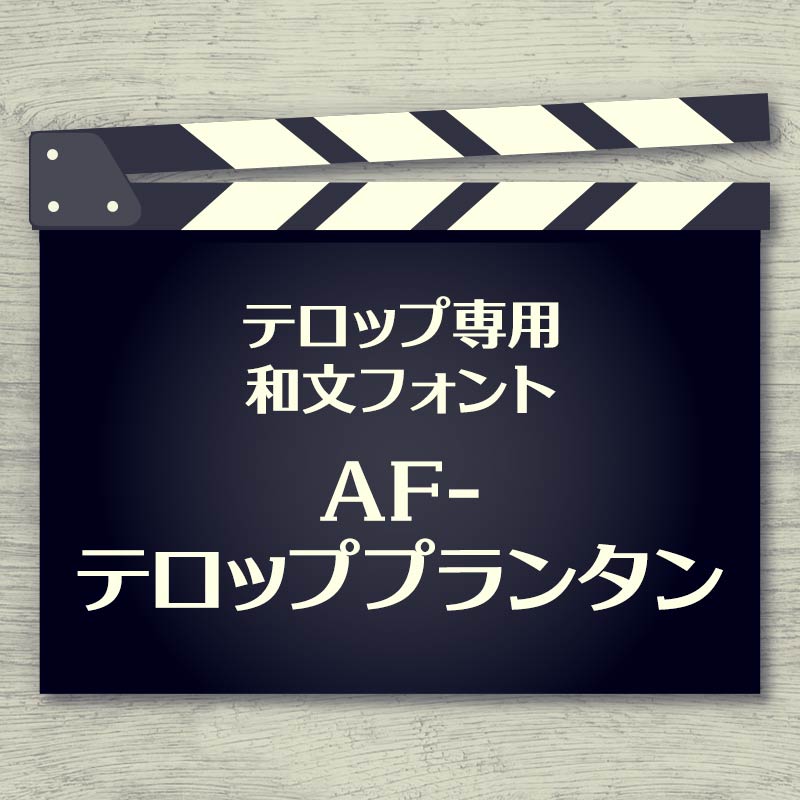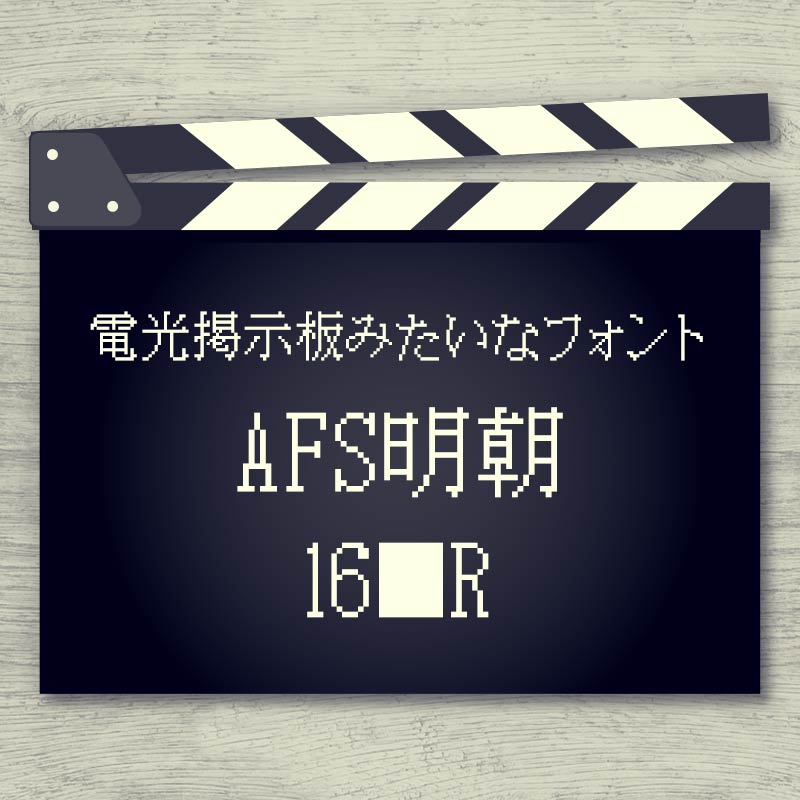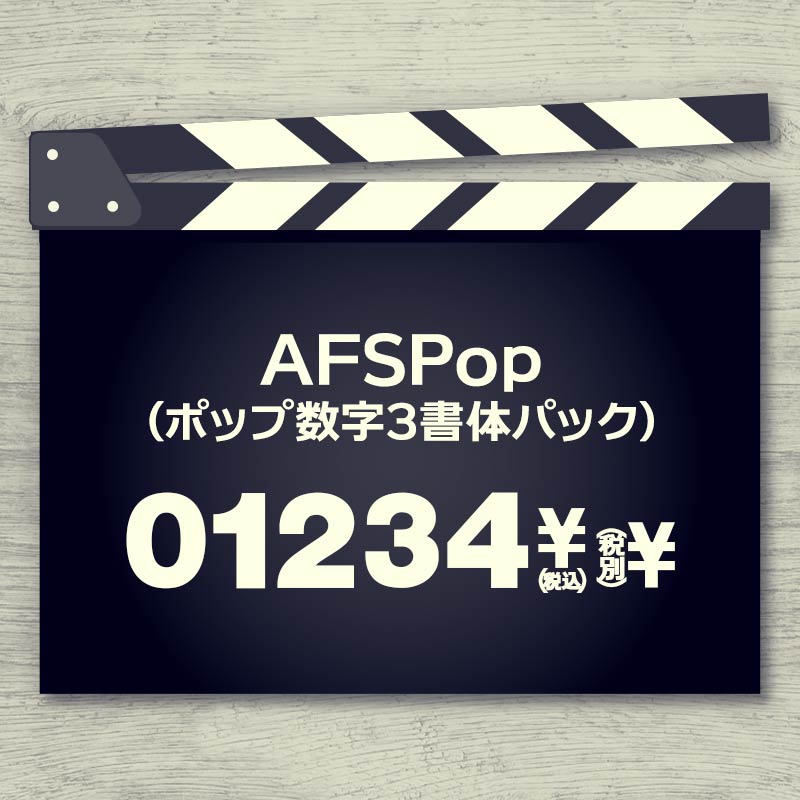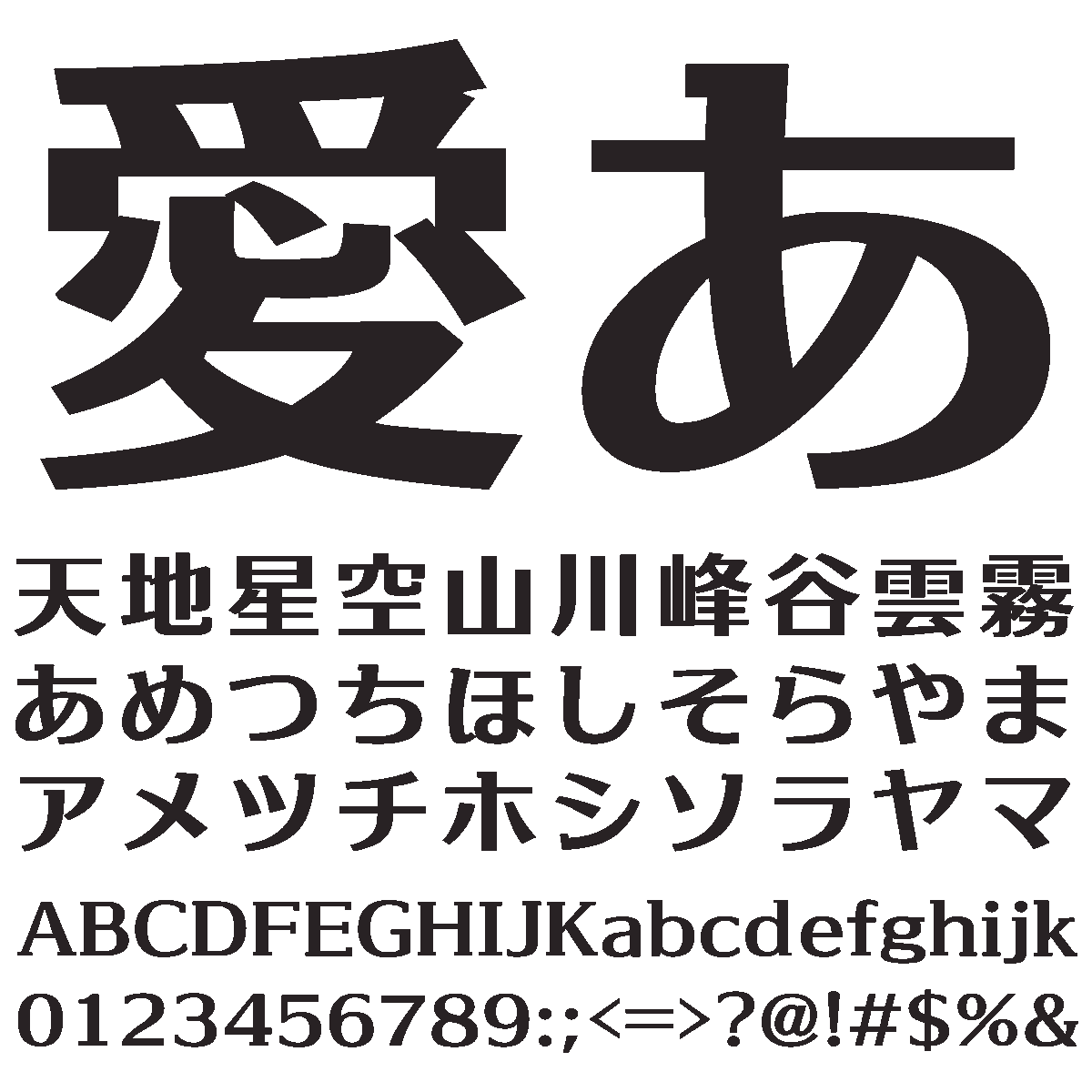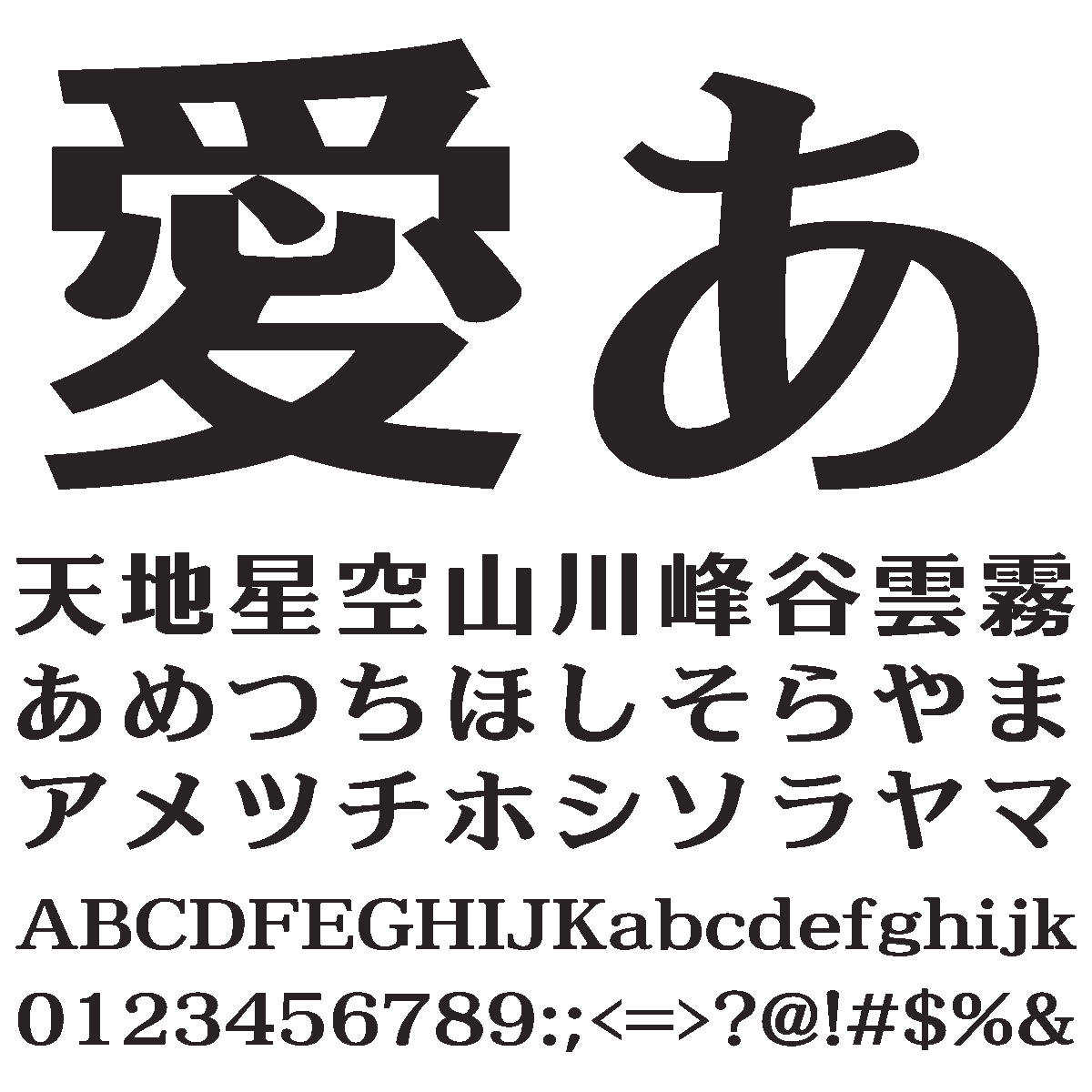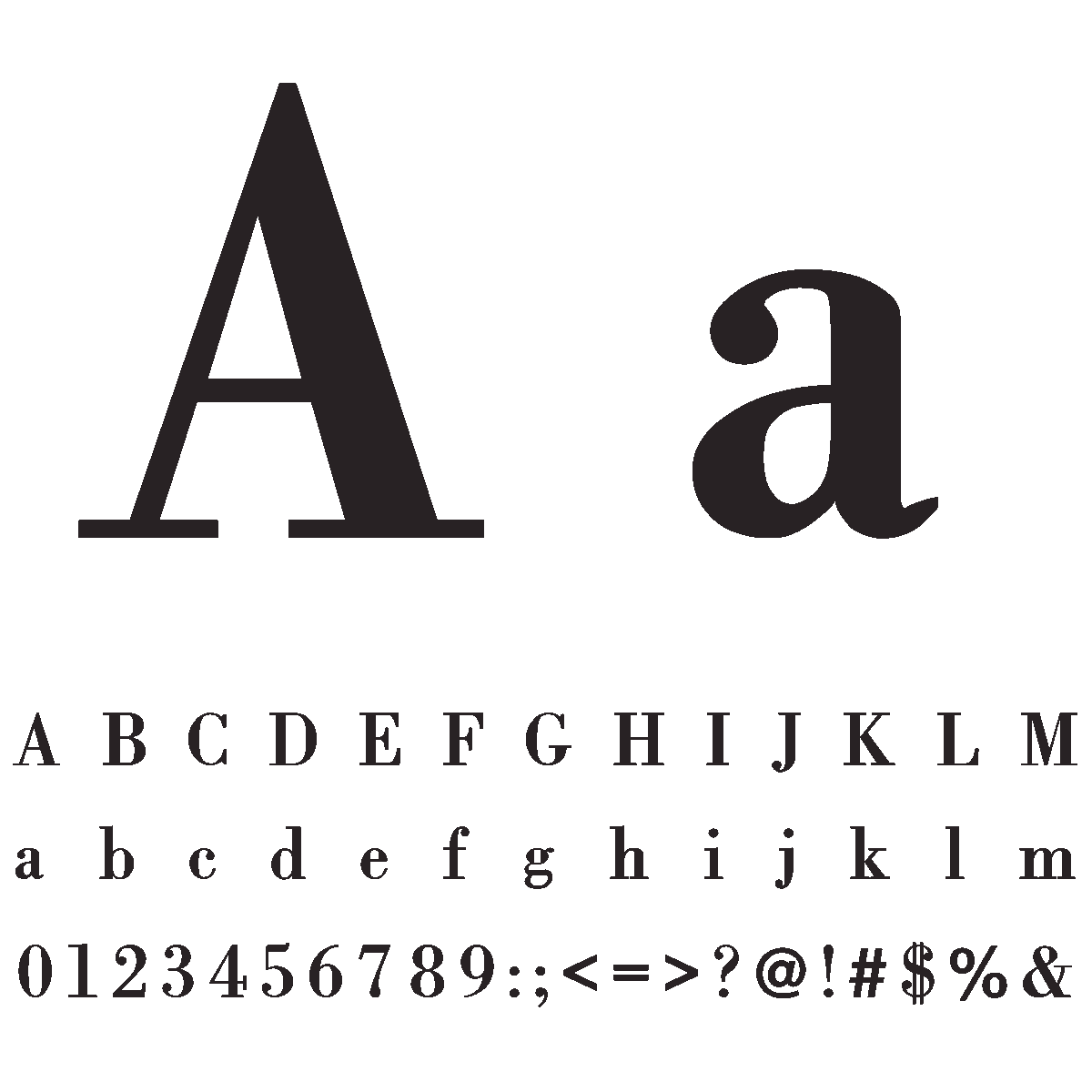
SNS動画編集で役立つフォント39セット
流行りのタテ型動画(YouTubeショート・TikTok・インスタリール)やYouTube動画制作の字幕やタイトル・感情を表すときにおすすめしたい39書体 (+特典1書体) を収録した特別セット
セット内容
●和文:19点
AFSまるご風10書体セット,テロップ/サムネイル用 AF-UVImpact,テロップ専用和文フォント AF-テロッププランタン・AF-テロップミンフォーマル,電光掲示板みたいなフォント AFS明朝16■R・AFSゴシック16■R,AFS漢字を作ろう
●平仮名:12点
AFS感情(平仮名)フォント12書体セット
●欧文:3点
テロップ専用復刻欧文 AF-TelopBod・AF-TelopEuro,AFS復刻欧文フォント AFSFutuM
●数字:3点
AFSPop (ポップ数字3書体パック)
●その他:2点
AFSDisplay (表示器風フォントシリーズ2書体パック)
●特典フォント (Windows用)
AFSデジタル放送TV用ARIB外字付きフォントDB (AFSARIBDB)
動画に文字や字幕を入れるメリット
動画編集にフォントを取り入れることで、さまざまなメリットと効果が期待できます。これから制作する動画をより魅力的にするために、フォントの選択を一度見直してみてください。それにより、動画の質が向上するかもしれません。
視覚的な強調
フォントは視覚的な要素で、視聴者の注意を引き、重要な情報を強調します。
情報の伝達
全ての視聴者が音声を聞くわけではありません。そのため、テキストは音声が聞こえない視聴者や異なる言語の視聴者にとって、情報を伝える重要な手段となります。
感情の伝達
フォントの種類やスタイルは、動画の雰囲気を伝える役割を果たします。例えば、楽しくカジュアルな雰囲気を出すためには、太く丸みを帯びたフォントが適しています。
視覚的な魅力と調和
動画におけるフォントは重要な視覚情報であるとともに、全体的なデザインとの調和も大切です。また、視聴者が情報を理解するためには、テキストは簡潔で明確であることが重要です。
おすすめの使い方
YouTube動画のサムネイル
使用フォント:AFSゴシックビューE_M
TikTokやshortsなどの縦型動画の文字入れ (字幕用フォント)
使用フォント:AF-テロッププランタンE2、AF-UVImpact、AFSゴシックドゥクラシックE_M
強いインパクトを与えたいシーン (装飾用フォント)
使用フォント:AFS感情-つらい、AFS感情-こわい
収録書体一覧
AFSまるご風 10書体セット
AFSオリジナルフォント35書体から10書体を厳選し丸ゴシック風の加工を施しました。
テロップ/サムネイル用 AF-UVImpact
ゲームソフトバンドル対応可能な、極太でインパクトあるユニバーサルフォントです。
元祖ユニバーサルデザインフォントであるメイリオを源流に、特徴が顕著に表れる一部の英数字ひらがなカタカナを一般的なUDフォントに近づけると共に、ひらがな字形ついては学参フォントを意識し視認性を強化しました。
テロップ専用和文フォント AF-テロッププランタン
加工フォントシリーズ (斜体/扁平/長体) に同梱されている「AFSPrintempsE.ttf (AFS-プランタンE)」の縦線をさらに太くし独立しました。
テロップ専用和文フォント AF-テロップミンフォーマル
加工フォントシリーズ (斜体/扁平/長体) に同梱されている「AFSミンフォーマルE (AFSMinformalE.ttf)」の縦線をさらに太くし独立しました。
電光掲示板みたいなフォント AFS明朝16■R
電光掲示板の雰囲気をアウトラインフォントで表現したフォント。街中で見られる電光掲示板のビットマップフォントをドットの形を■で表現した電光掲示板っぽい明朝フォントです。
電光掲示板みたいなフォント AFSゴシック16■R
電光掲示板の雰囲気をアウトラインフォントで表現したフォント。街中で見られる電光掲示板のビットマップフォントをドットの形を■で表現した電光掲示板っぽいゴシックフォントです。
AFS漢字を作ろう 4書体セット
Illustratorを使い自分好みの漢字や創作漢字が作れるストロークフォントです。
漢字を構成する部首 (へんやつくり) だけでなく、へんそのものを構成するエレメントを分解することが出来ます。
AFS感情(平仮名)フォント12書体セット
感情をイメージした平仮名フォント。つらい、うれしい、いいね、おこる、すごい、ださい、うるさい、かなしい、わらい、こわい、たのしい、やった、以上12感情をそれぞれTTFひらがなフォントにした12書体パックです。
この製品は平仮名専用フォントです。
テロップ専用復刻欧文 AF-TelopBod
縦横の差が大きめで、見出し用としてインパクトを与える欧文フォントです。
テロップ専用復刻欧文 AF-TelopEuro
ユーロスタイル風なサンセリフ、1Byte欧文デザインフォントです。
AFS復刻欧文フォント AFSFutuM
歴史的に重要且つ著名な欧文を活字印刷から刻まれた雰囲気を残しデジタルフォントへ。1924年パウル・レンナーによるフーツラ・グロテスクの復刻。
AFSPop (ポップ数字3書体パック)
AFSPopは、インパクトがあり視認性に優れたポップ用数字3書体セットです。